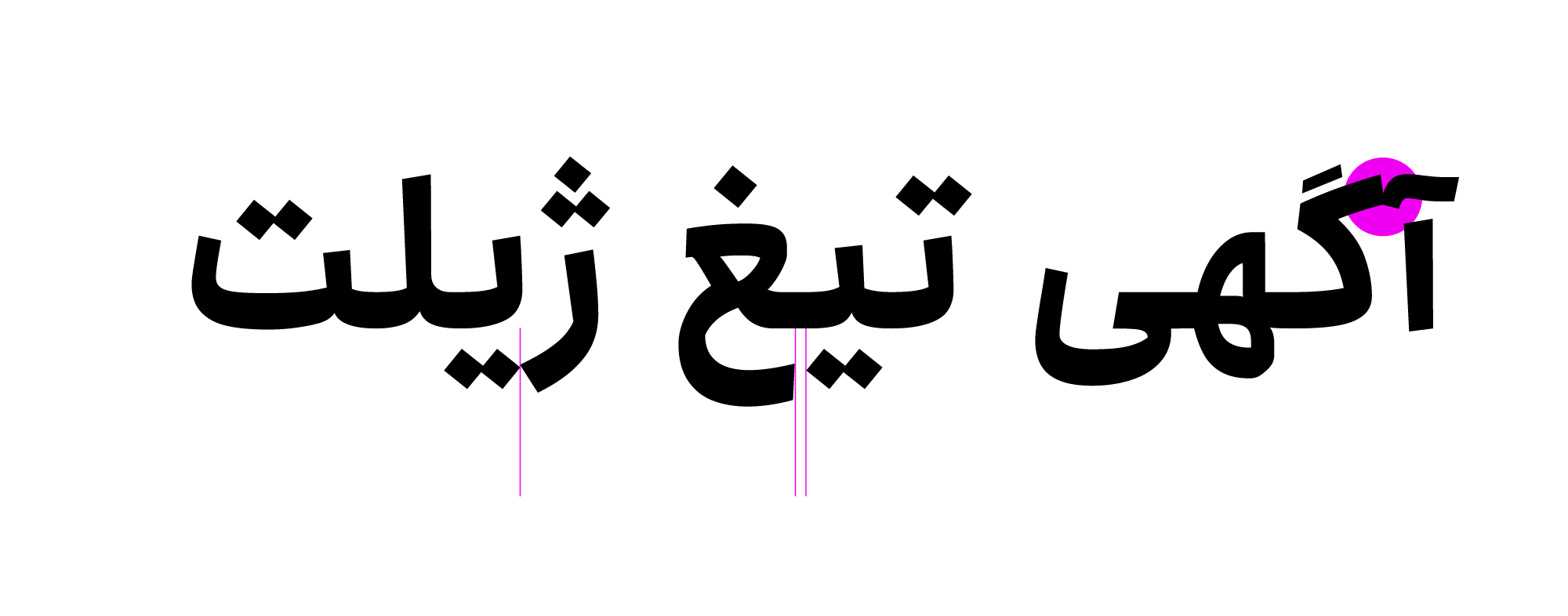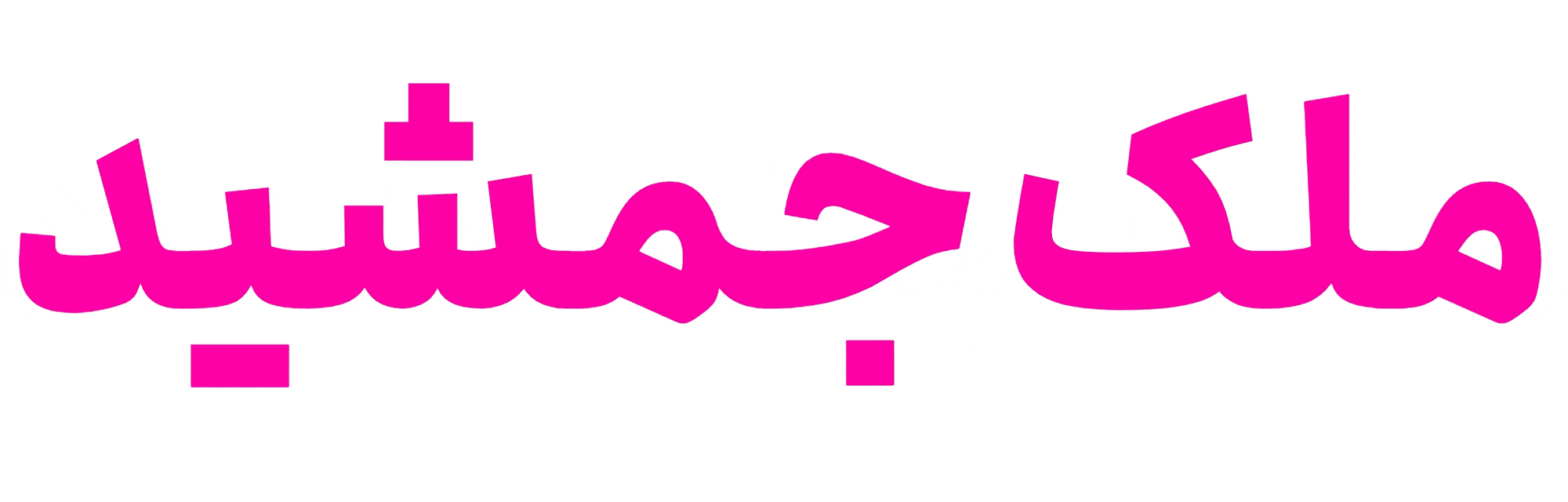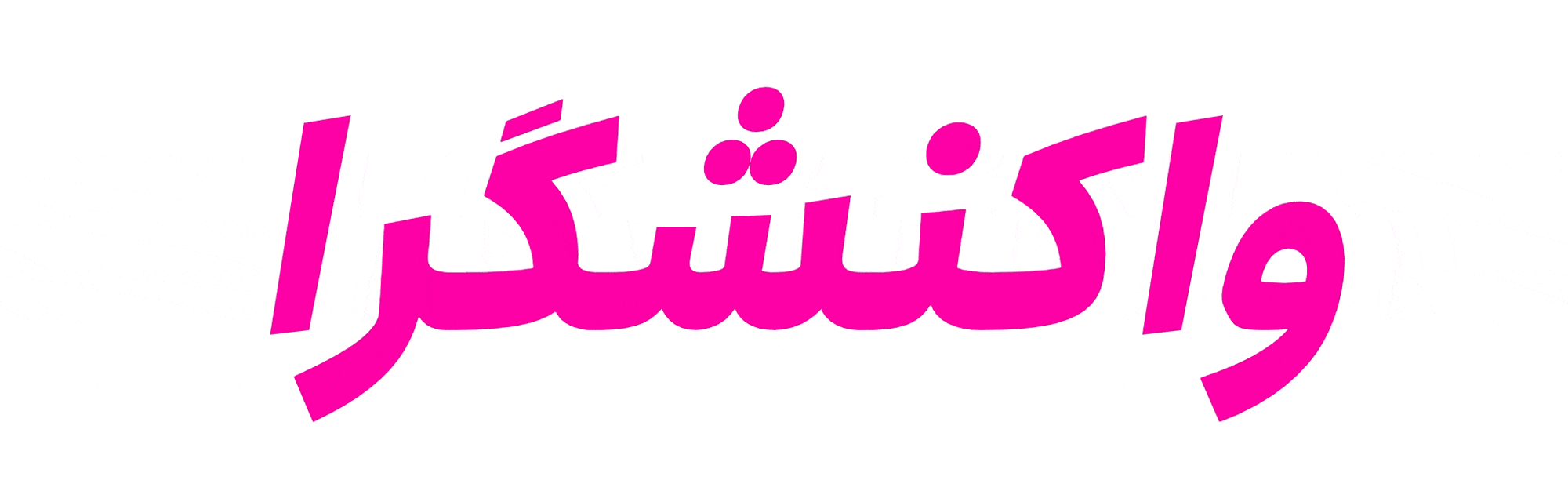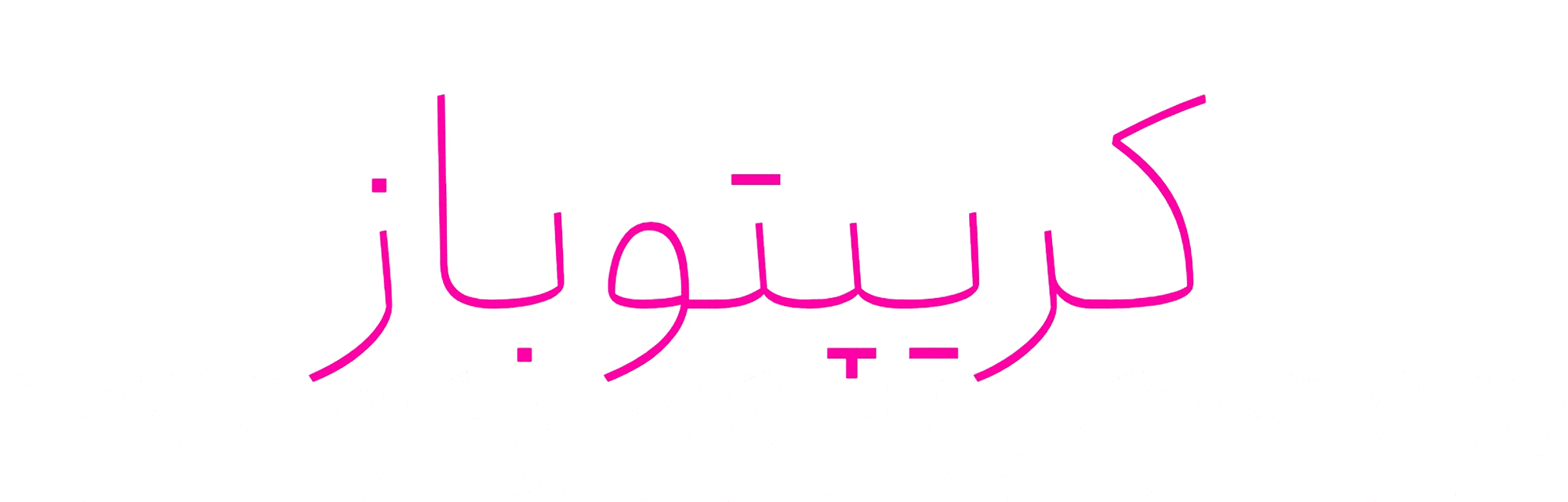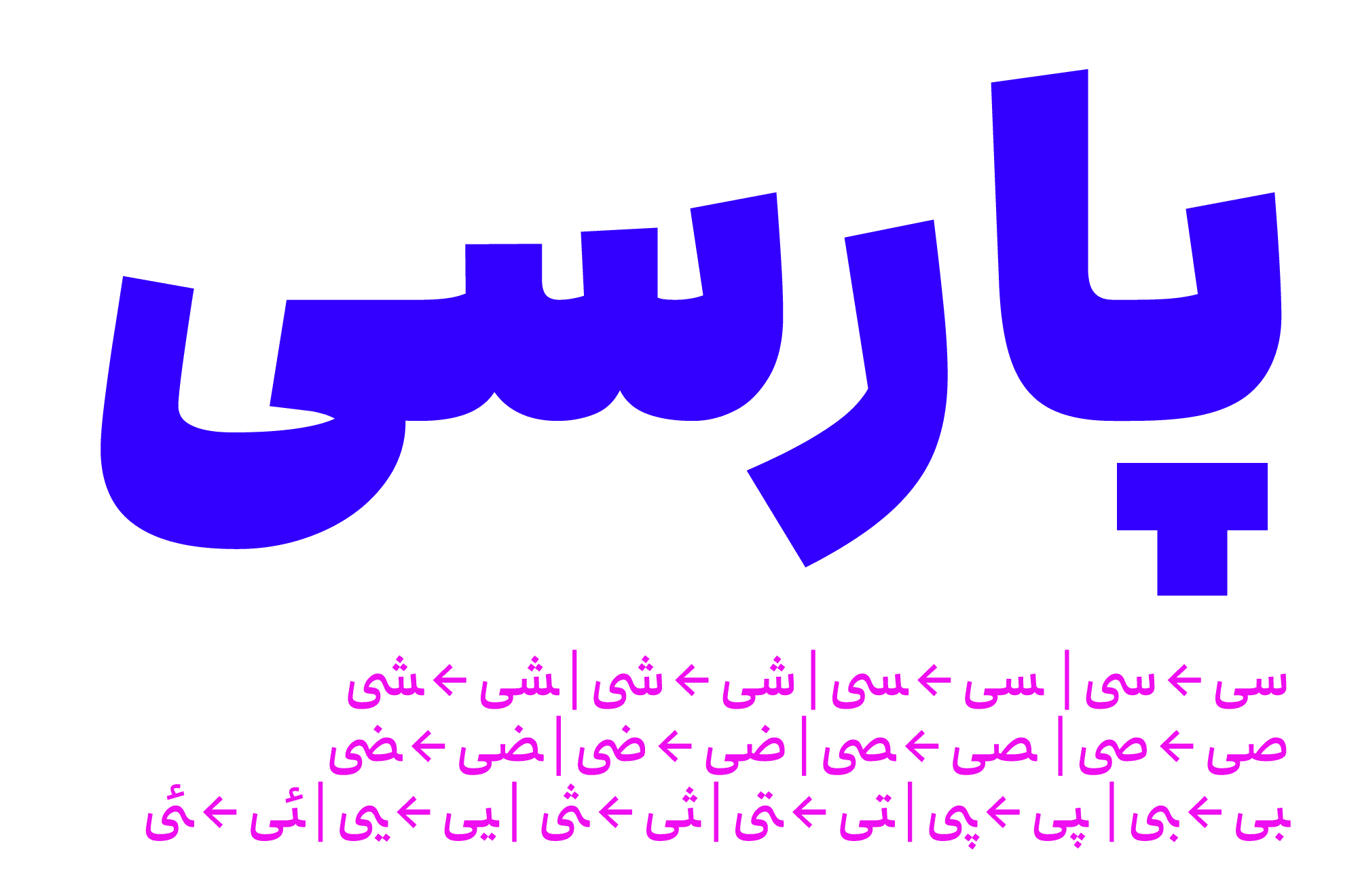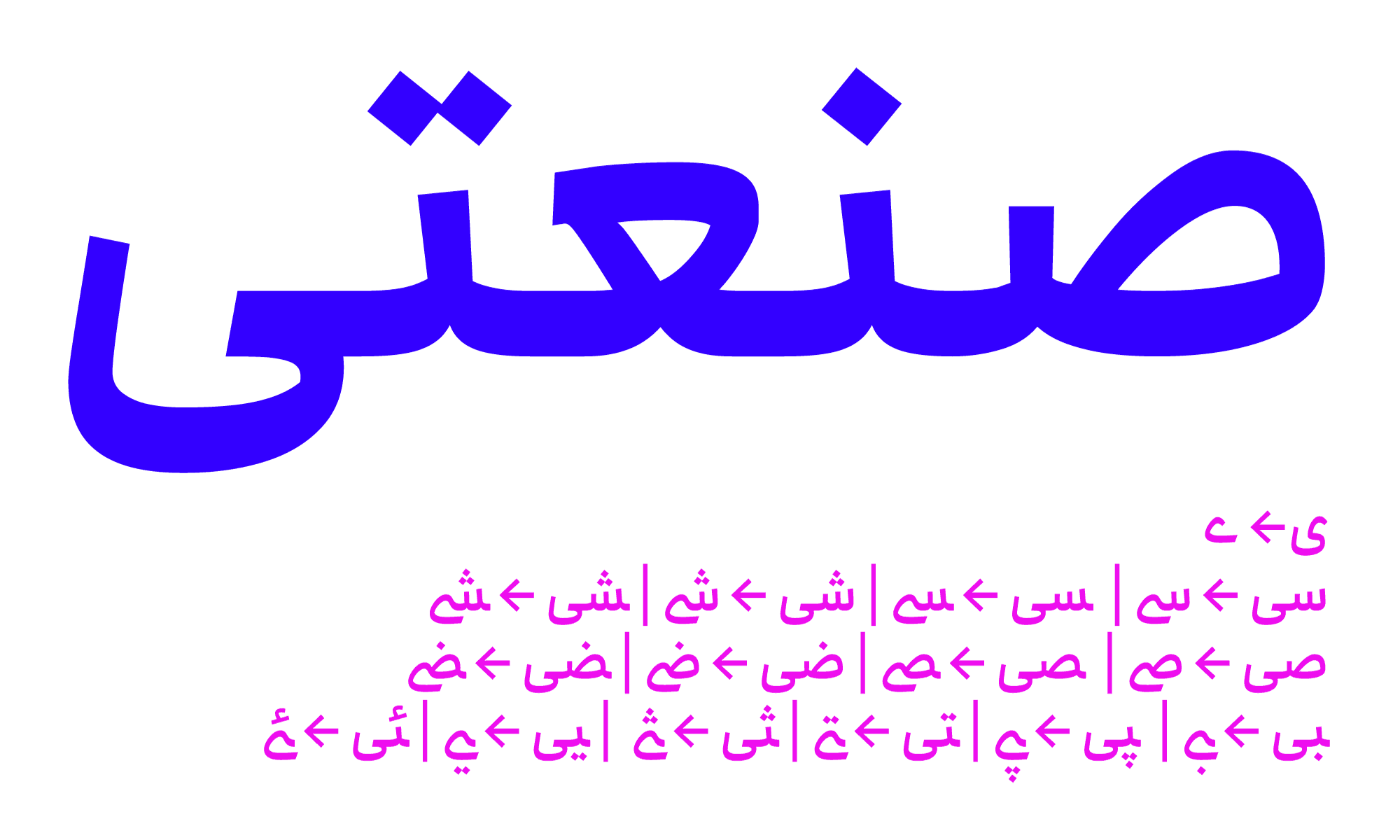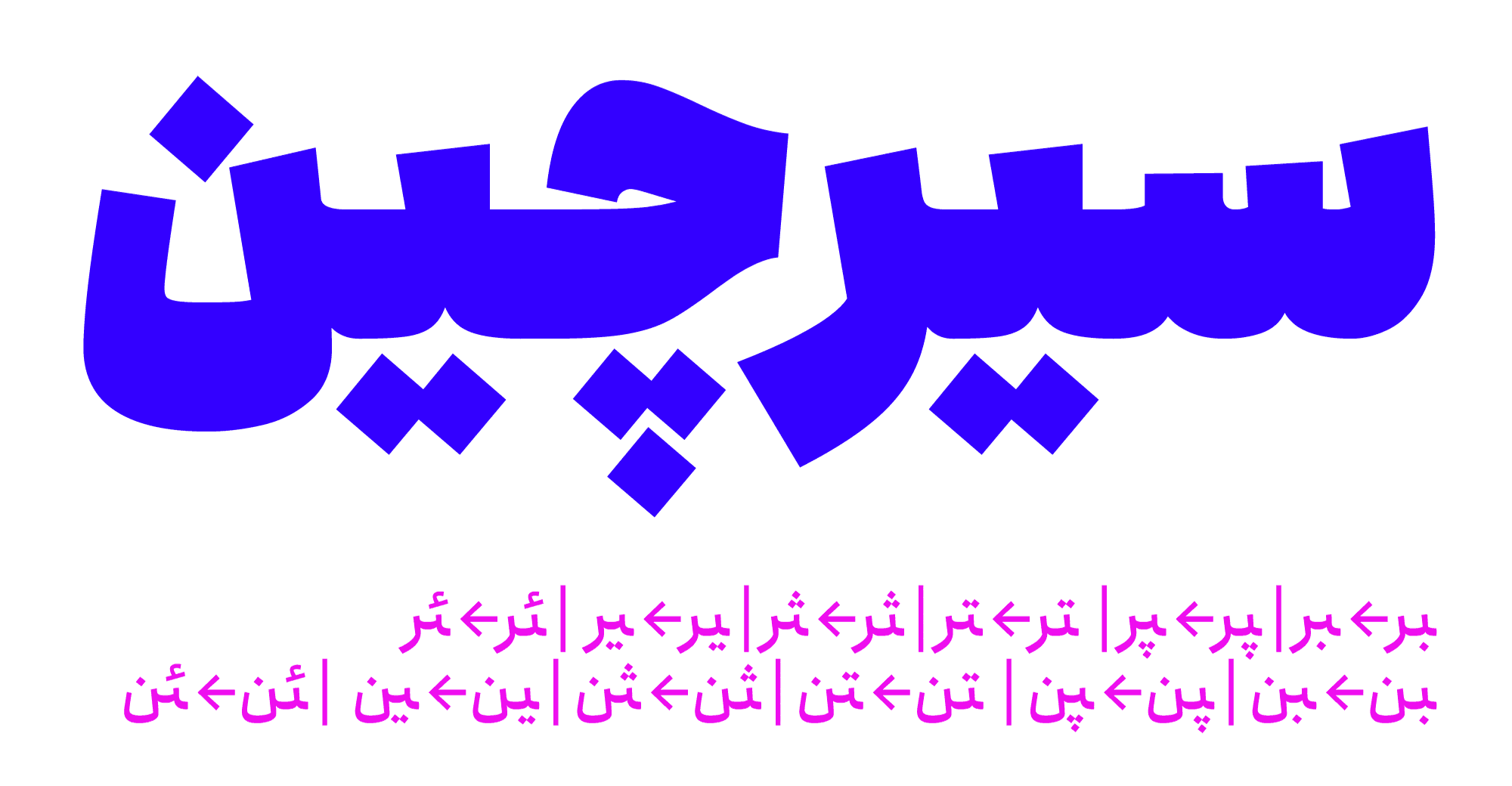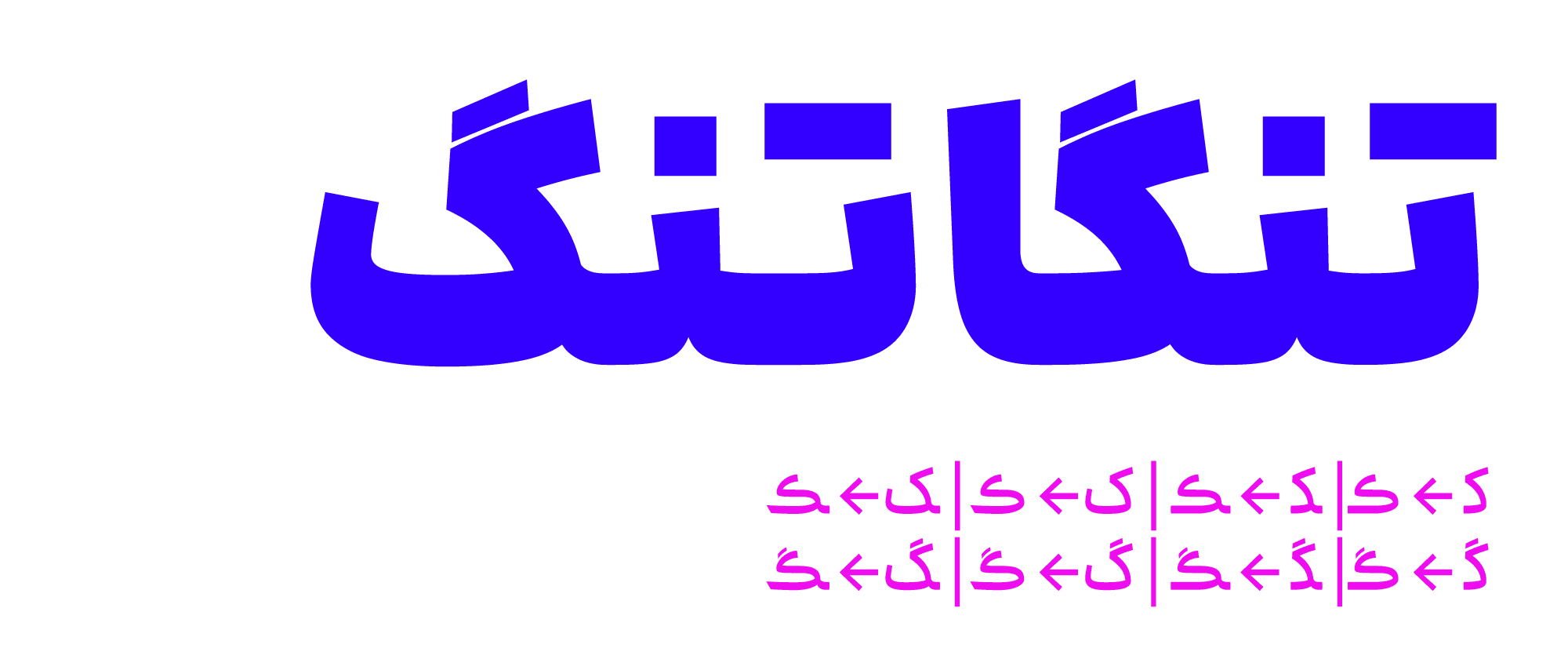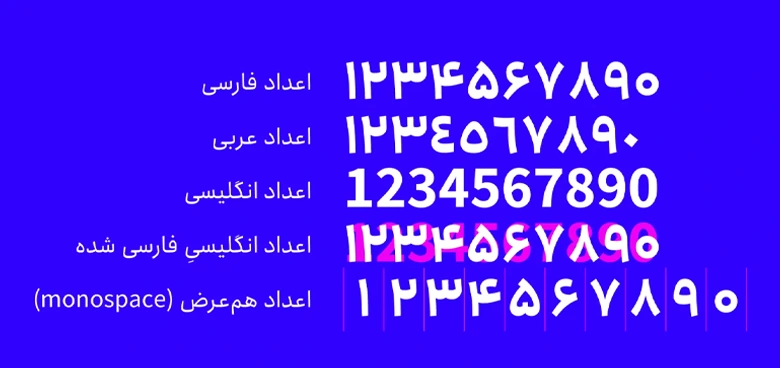
فونت انجمن (Anjoman)
فونت انجمن (به انگلیسی: Anjoman) از جمله فونت‌های فارسی مناسب متن است که دارای طراحی سنس بوده و برای استفاده در محیط‌های مختلف وب و فضای آفلاین کاربردهای متنوعی دارد. فونت انجمن رایگان نیست و با تنوع بسیار بالای وزنی، پشتیبانی از نسخه وریبل و سرشار از حروف جایگزین که دارد در ۳ بسته مختلف قابل خریداری است.
هیربد لطفیان این فونت را با حمایت انجمن صنفی طراحان گرافیک ایران به‌صورت کاملا اختصاصی طراحی کرده است که از چندین زبان ختلف پشتیبانی کرده و تمامی حروف، اعراب، کاراکترهای خاص، گلیف‌ها و سمبل‌ها در هر دو زبان‌های خاورمیانه‌ای و لاتین دارای طراحی اختصاصی هستند.
در ادامه این نوشته از وبسایت فونتچی به نقد و بررسی کامل فونت انجمن خواهیم پرداخت. این فونت از جمله فونت‌های با تنوع بسیار بالا و با اصالت است که هرساله به‌روزرسانی می‌شود و در آخرین نسخه به‌روز شده که با نام فونت انجمن مکس (Max) شناخته می‌شود، نسخه متغیر آن از قابلیت ایتالیک (Italic) و فشرده (Condense) کردن حروف نیز پشتیبانی می‌کند.
معرفی و بررسی فونت انجمن (Anjoman)
از جمله کاربردهای فونت انجمن می‌توان به استفاده در رابط کاربری اپلیکیشن و سایت، طراحی‌های گرافیک محیطی و تبلیغاتی، بسته‌بندی محصولات، صفحه‌آرایی کتاب‌ها و مطبوعات و ده‌ها مورد دیگر اشاره کرد.
تنوع بسیار بالایی که این فونت از نظر وزنی و نسخه متغیر دارد، طیف وسیعی از نیازها را برای استفاده در فونت عنوان، متن، شعار، تبلیغات و رابط کاربری فراهم کرده است که از همین‌رو بسیاری از سازمان‌ها که نیاز به ساختاری یکپارچه از نظر طراحی فونت و رابط کاربری دارند به سراغ این فونت می‌آیند.
سبک طراحی و وزن فونت انجمن
تمامی این وزن ها با ساختاری نزدیک به هم و مکمل‌کننده یکدیگر طراحی شده‌اند که در طراحی یک رابط کاربری به هماهنگ کردن بیشتر کمک می‌کنند. فونت‌های لاغر فونت‌های چاق را تکمیل می‌کنند تا آنها نیز دیده شوند و برعکس فونت‌های چاق و بسیار ضخیم هم مکمل کننده فونت‌های لاغر هستند تا در میان انبوه طولانی از متن‌های بلند مورد بی توجهی قرار نگیرند.
ویژگی و امکانات فونت Anjoman
انجمن را می‌توان یکی از بهترین فونت‌های وب فارسی معرفی کرد که علاوه‌بر پشتیبانی از چند زبان و وزن مختلف، نسخه متغیر ان برای استفاده در هر صنعتی چه در فضای آفلاین و چه فضای دیجیتال کاربردهای خود را داشته و نقش بسیار پررنگی را ایفا می‌کند.
تفاوتی ندارد که از انجمن برای طراحی صفحات وب استفاده کنید یا اینکه از آن در جهت طراحی بیلبوردهای تبلیغاتی و محیط استفاده کنید. در تمامی کاربردها تنوع وزن و متغیرهایی که برای تغییر سبک نوشتار این فونت دارد، به ایجاد طرح‌هایی خلاقانه بدون نیاز به درگیر شدن با نرم‌افزارهای گرافیکی در اختیارتان قرار می‌دهد.
پشتیبانی از ۵ زبان مختلف
فونت انجمن از ۵ زبان مختلف پشتیبانی می‌کند که همه این زبان‌ها دارای استانداردهای خاص خود هستند؛ از همین رو کلیه اعداد، اعراب، سمبل‌ها و تفاوت‌هایی که به شکل جزئی در زبان‌های خاورمیانه‌ای وجود دارد، به‌طور کامل در آن رعایت شده است.
فونت فارسی انجمن جدایی از این زبان از زبان‌های کردی، عربی، اردو و انگلیسی پشتیبانی می‌کند. پشتیبانی از زبان‌های خاورمیانه‌ای که بر اساس استاندارد حروف فارسی هستند محدود به این زبان‌ها نیست؛ در نتیجه برای زبان کردی و ترکی با تایپ فارسی هم می‌توان از این فونت استفاده کرد. اما ممکن است برخی ساختارها گلیف‌های برخی زبان‌ها را نداشته باشند.
سبک طراحی فونت انجمن انگلیسی در سبک سن‌سریف طراحی شده است. از همین رو حروف انگلیسی هم‌نشین «انجمن» با استفاده از خانواده حروف Source Sans Pro و تحت مجوز OFL توسعه یافته و دارای تغییرات جزئی برای هماهنگی بهتر با نسخه فارسی و عربی است.
دارای حروف و ترکیبات جایگزین در ۴ سبک
با دانلود فونت anjoman به یکی از معدود فونت‌هایی دسترسی خواهید داشت که ترکیبات و حروف جایگزین در نسخه وریبل، با استفاده از دستوراتی که در دل فونت جای داده شده برای وب نیز به‌سادگی قابل استفاده است. این ترکیبات شامل «ی، ـی، ـر، ـن، ک، گ» می‌شود که امکان استفاده از آنها را در حالت‌های زیر خواهید داشت.
سبک اول که با نام StylisticSet ۰۱ شناخته می‌شود با استفاده از متغیر SS01 قابل استفاده است. این متغیر تنظیمات OpenType را در حالتی که کلمات به «یای آخر» ختم شده باشند، مانند تصویر بالا تغییر خواهد داد.
سبک دوم که با نام StylisticSet ۰۲ شناخته می‌شود با استفاده از متغیر SS02 قابل استفاده است. این متغیر تنظیمات OpenType را در حالتی که کلمات به «یای آخر» ختم شده باشند، مانند تصویر بالا تغییر خواهد داد.
سبک سوم که با نام StylisticSet ۰۳ شناخته می‌شود با استفاده از متغیر SS03 تنظیمات OpenType را برای مواقعی که نیاز به تغییر اتصال دندانه‌ها به «‍ر،‍ ‍ز، ‍ژ» و «‍ن» نیاز داشته باشید فراهم خواهد نمود.
و در نهایت در سبک سوم که با نام StylisticSet ۰۴ شناخته می‌شود با استفاده از متغیر SS04 تنظیمات OpenType برای حروف «ک، گ» قابل تغییر است که می‌توانید این حروف را مشابه با ترکیبات بالا به صورت تکی یا ترکیبی در ابتدا، میانه یا انتهای کلمات تغییر دهید.